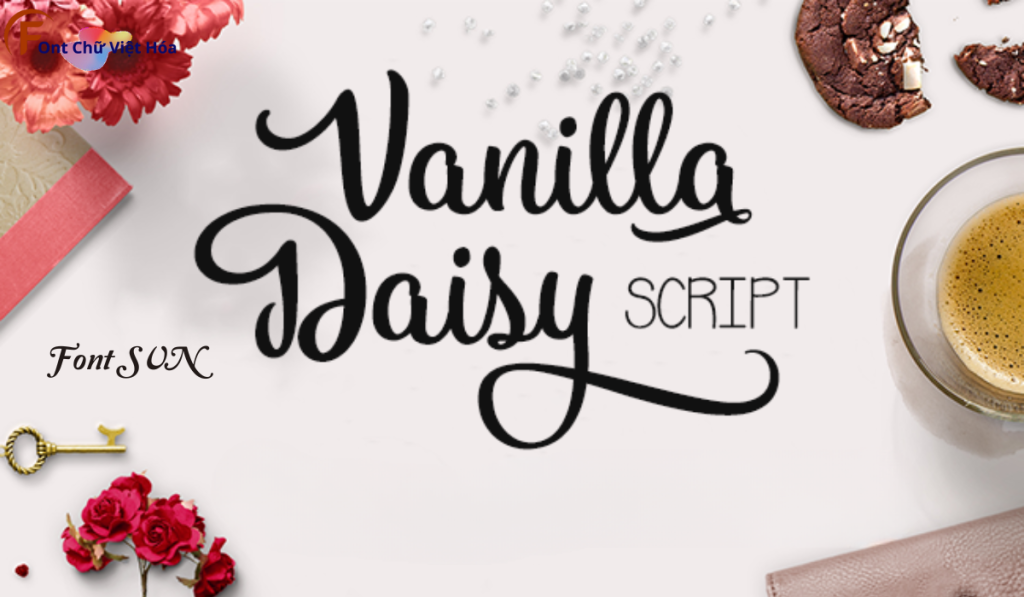
Font SVN Vanilla Việt Hoá
Tác giả: SVN Vanilla
Ngôn ngữ: Tiếng Việt, Tiếng Anh
Bộ Font: SVN
Phân loại: Cá tính, Độc đáo
Độ dày: Mỏng, Thường, Đậm
Font SVN Vanilla Việt Hoá là một font chữ không chân hiện đại, thuộc bộ font SVN. Được thiết kế với mục tiêu mang lại sự tinh tế và thanh lịch, font này phù hợp cho các dự án thiết kế như website, tài liệu, và bao bì sản phẩm. Với các nét chữ rõ ràng và độ dày đều đặn, Font SVN Vanilla Việt Hoá không chỉ dễ đọc mà còn tạo cảm giác chuyên nghiệp. Việc Việt hóa font giúp người dùng dễ dàng sử dụng trong các thiết kế tiếng Việt, mang lại sự tiện lợi và thẩm mỹ cao.